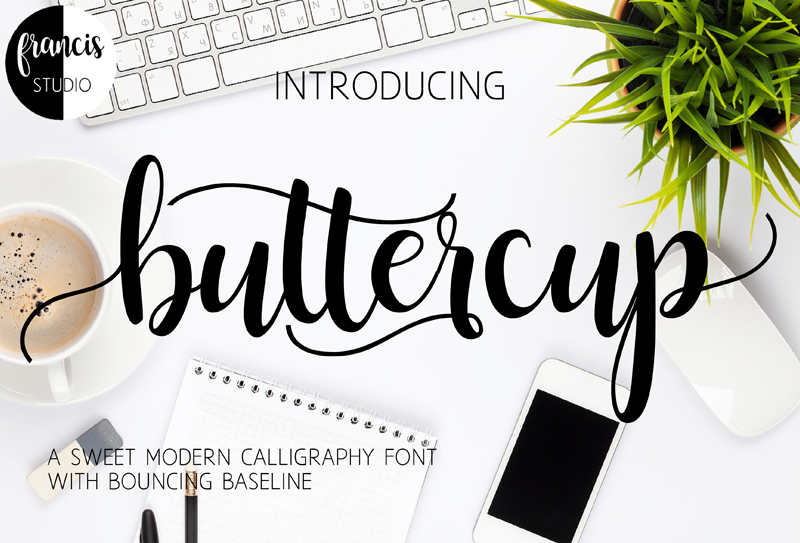
Buttercup Script Font – Fonte Grátis
Buttercup Script Font
A ‘Buttercup Script Font’ é uma graça elegante para letrinhas florais feitas por Hamilton. Inspirada em frutas cintilantes, esta fonte oferece um toque delicado e sofisticado às criações digitais. Ela combina perfeitamente com o estilo de design Brush Fonts, criando texturas suaves que se adaptam à maioria das aplicações. É uma ótima escolha para designers gráficos que buscam adicionar um toque elegante e único a seu trabalho. Com uma licença personalizada exclusiva para uso pessoal, esta fonte traz vida às suas criações digitais. Acreditamos que cada designer tem algo especial a oferecer, então estamos aqui para apoiar você no desenvolvimento de projetos únicos. Se tiver alguma pergunta, reação ou comentário sobre a ‘Buttercup Script Font’, não hesite em entrar em contato conosco através do email . Nossa equipe está pronta para ajudá-lo o mais rápido possível. Agradecemos sua atenção e esperamos que a ‘Buttercup Script Font’ seja uma fonte de inspiração para seus projetos.